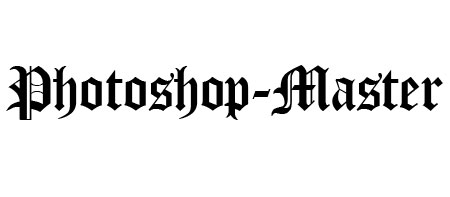
AngeDemon, шрифт не работет на том или ином языке. Так бывает. Например этот шрифт только на англ. по-моему
жалко русский не поддерживает
Шрифт, вроде бы, не плохой, но качать не буду.
ПРИКОЛЬНО что сказать
Красивый шрифт)))
AngeDemon, шрифт не работет на том или ином языке. Так бывает. Например этот шрифт только на англ. по-моему
о прикольный шрифт скачаю
Моя любимая игра, GTA. Клёво.
подскажите как перевести этот шрифт на русский язык либо такой же ,но русский шрифт помогите найти ,очень нужно.заранее спасибо!
Death Note *о*
Вааа шрифт как из Тетради Смерти 8О8 Наконец то я его нашла XDDDD
Супер шрифт!)
шрифт тетрадки! О_О
шрифт из тетрадки *0*
похож на шрифт из тетради смерти *______________*
солидный шрифт
клас
толко один варянт, нету курсив жирный
Похож на Old English... )
Этож шрифт как с тетради смерти :3
Шрифт шикарный))